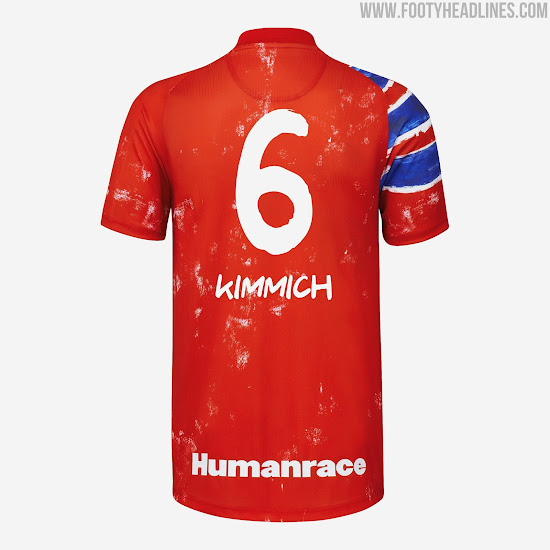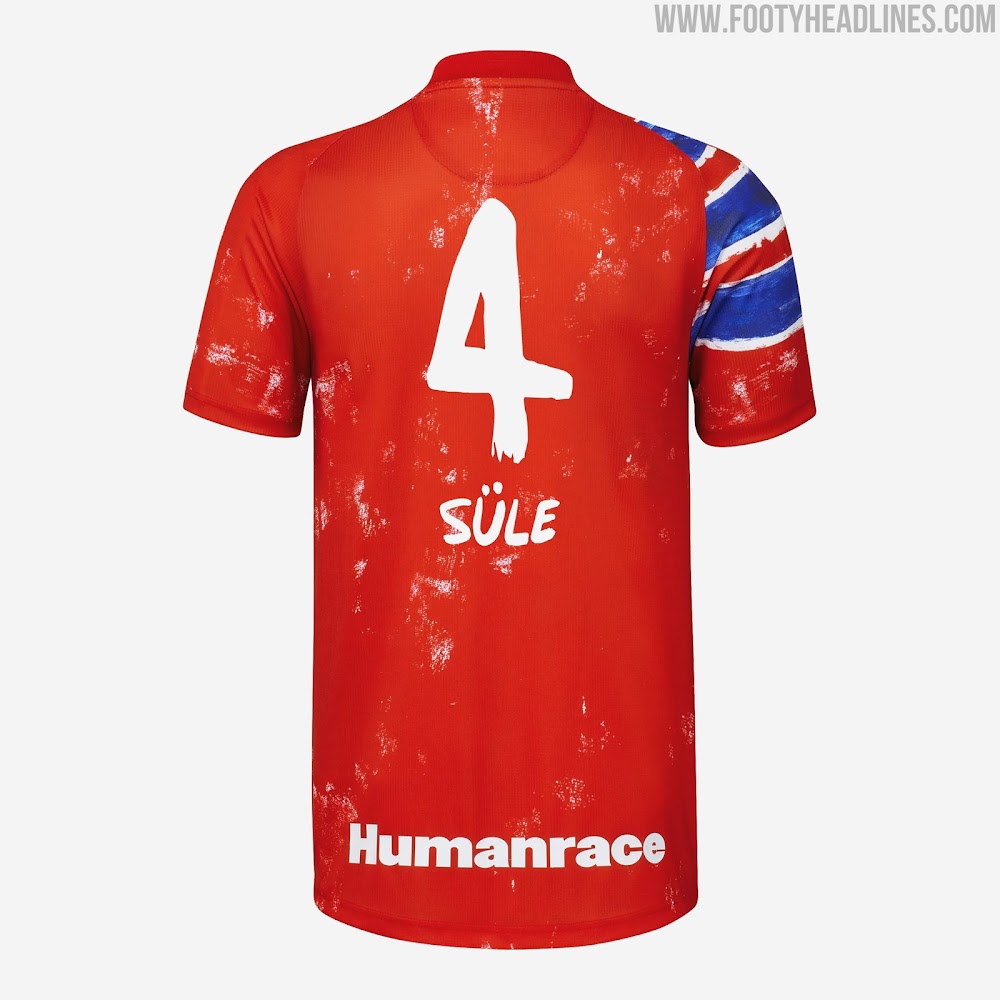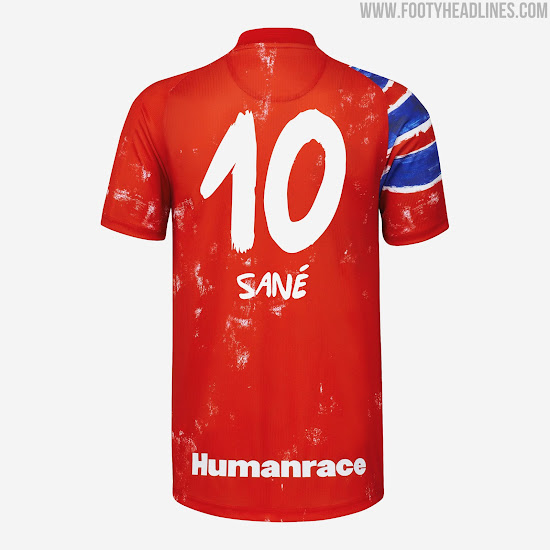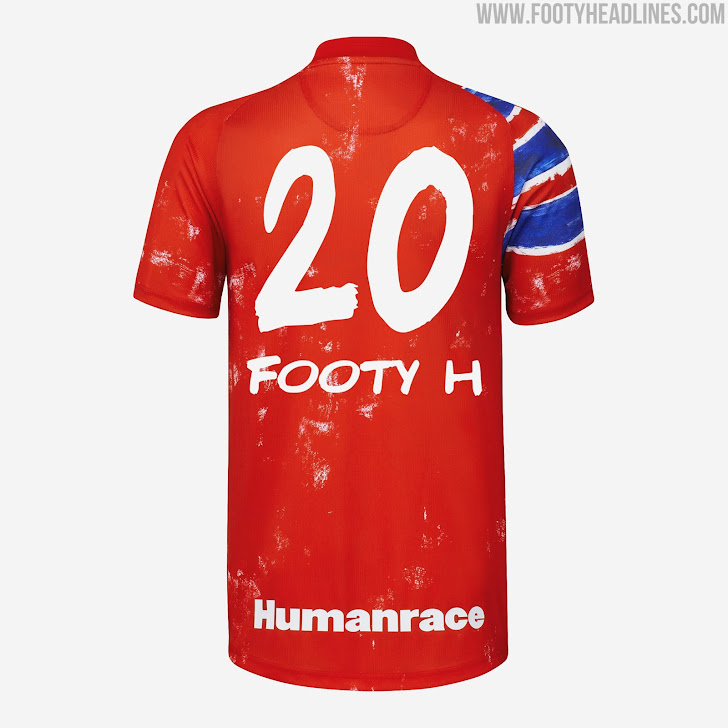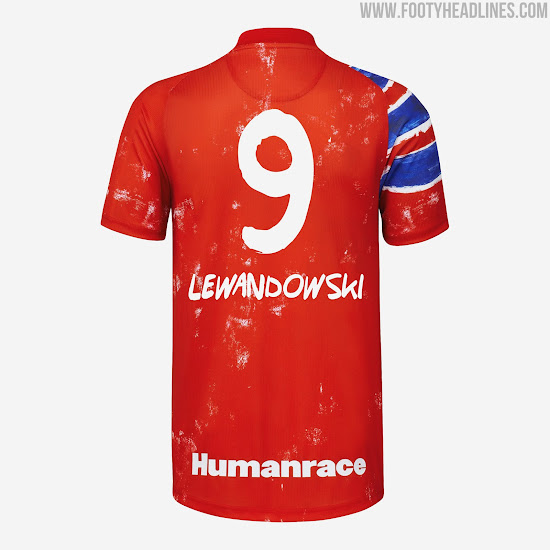
Adidas Humanrace 2020 Trikot-Schriftart veröffentlicht
Im Online-Shop von Bayern München erhalten wir einen ersten Blick auf die Schrift, die für die Adidas x Pharrell Williams Humanrace 2020 Trikots entworfen wurde.
Adidas Humanrace 2020 Trikot-Schriftart
Die Adidas Humanrace 2020 Trikot-Schrift wurde vor der Digitalisierung von Hand gezeichnet. Dadurch ist die Schrift einzigartig im Vergleich zu anderen Schriften und passt perfekt zum Stil des Trikots.
Die Adidas Humanrace Trikot-Schrift wird im nächsten DFB-Pokal-Spiel der Bayern debütiert.
Juventus verwendete die Trikot-Schrift nicht, als sie ihr 2020er Humanrace-Trikot präsentierten - sie mussten die stromlinienförmige Schrift der Serie A verwenden.